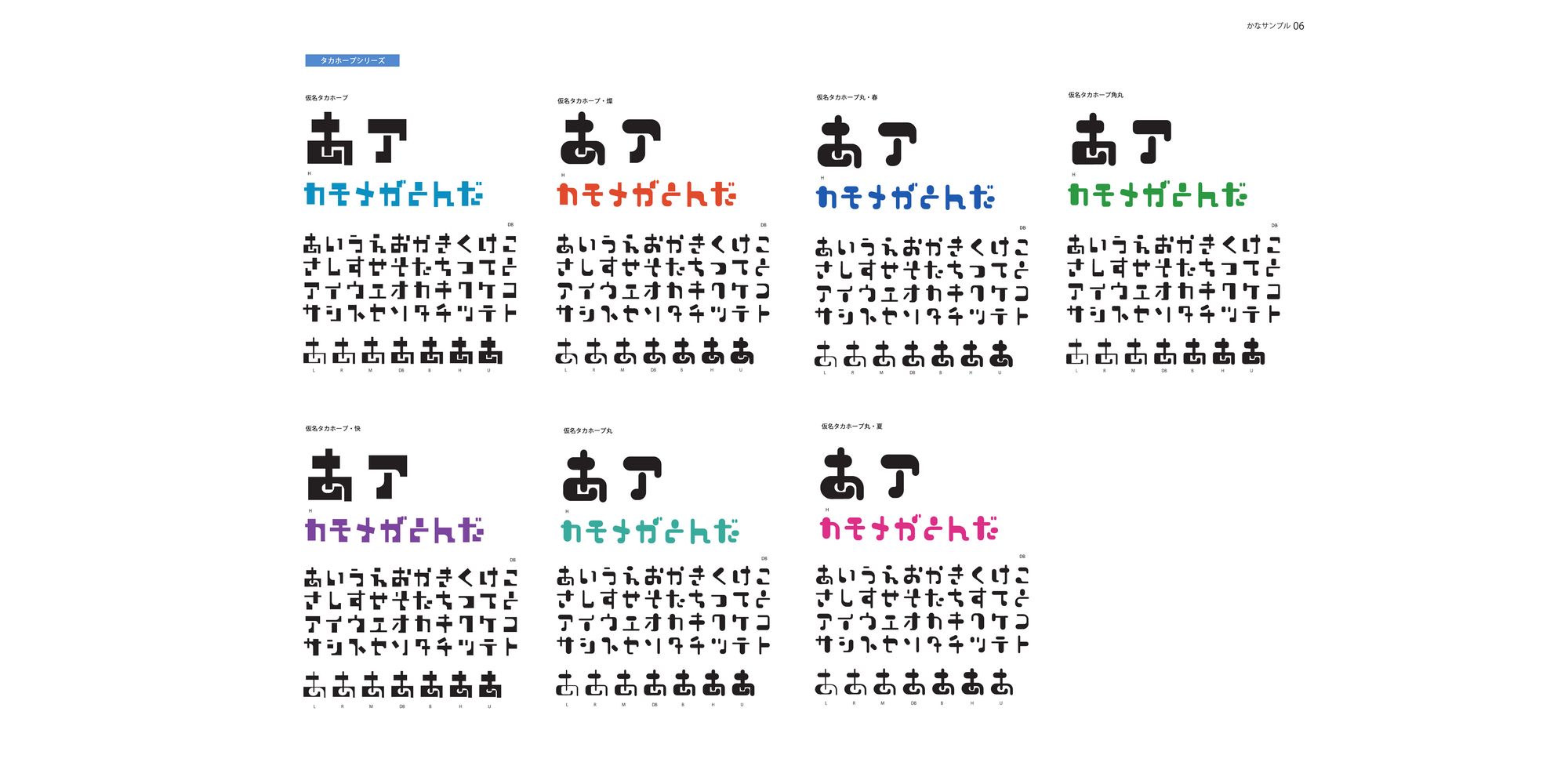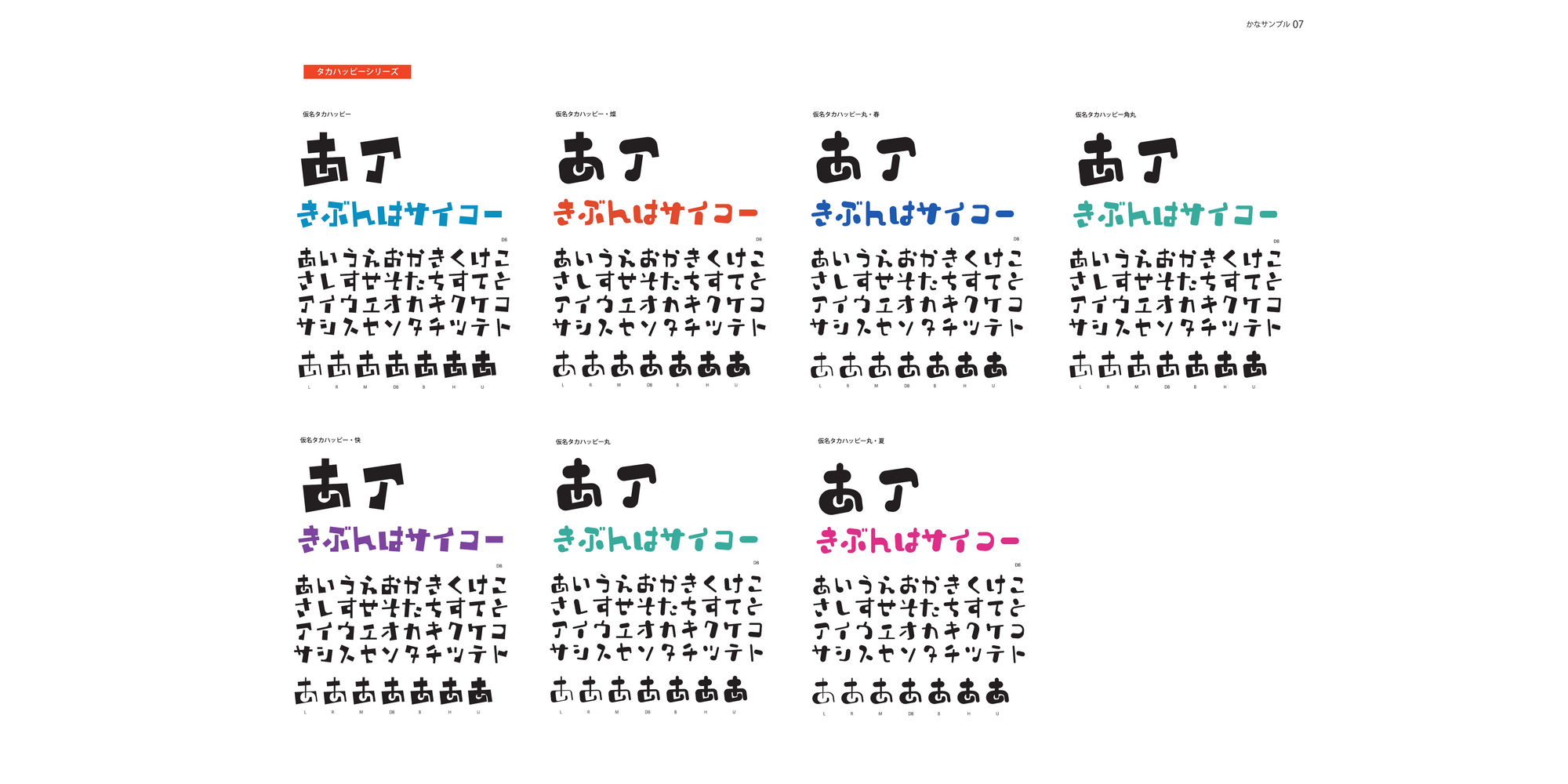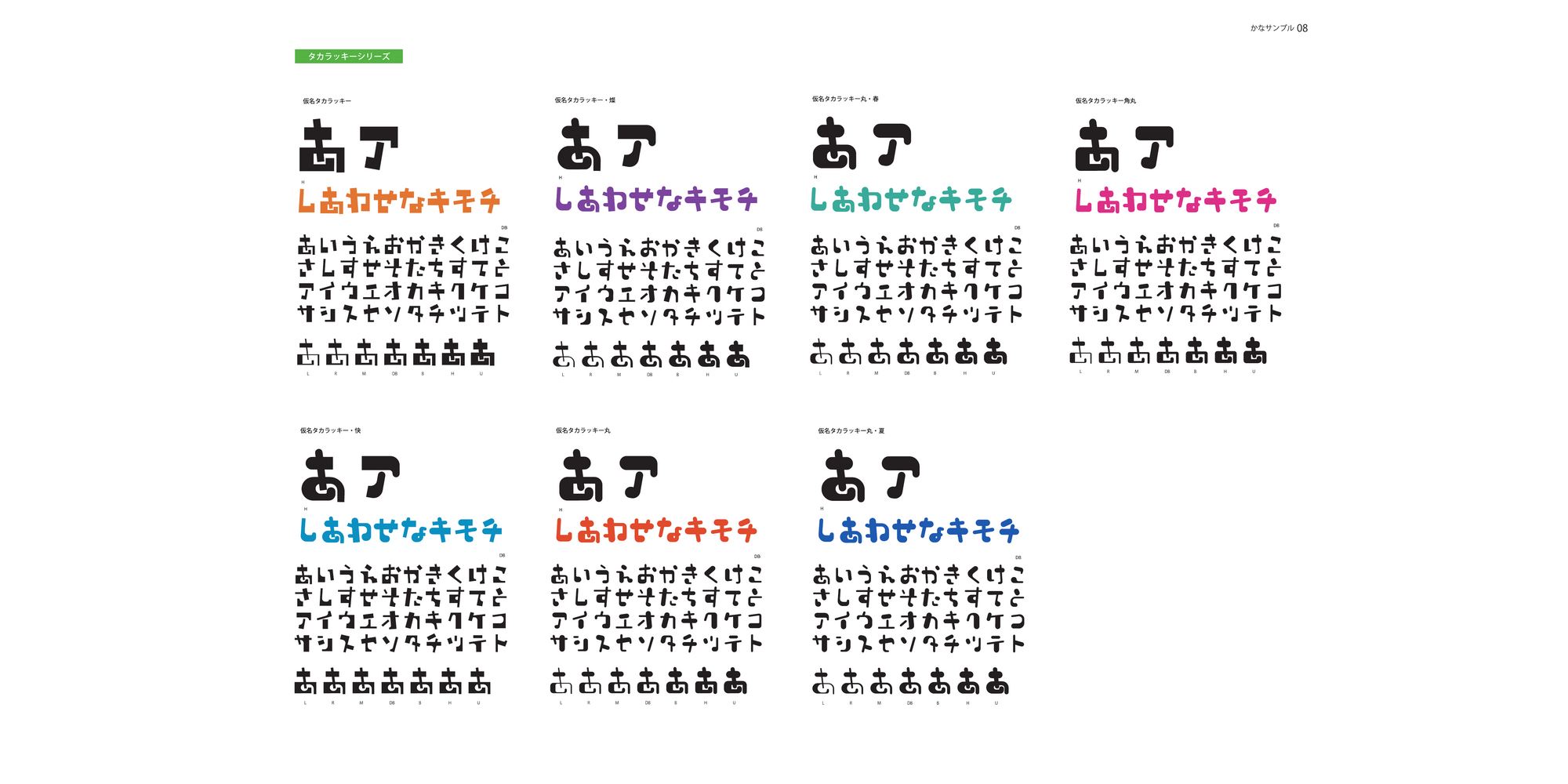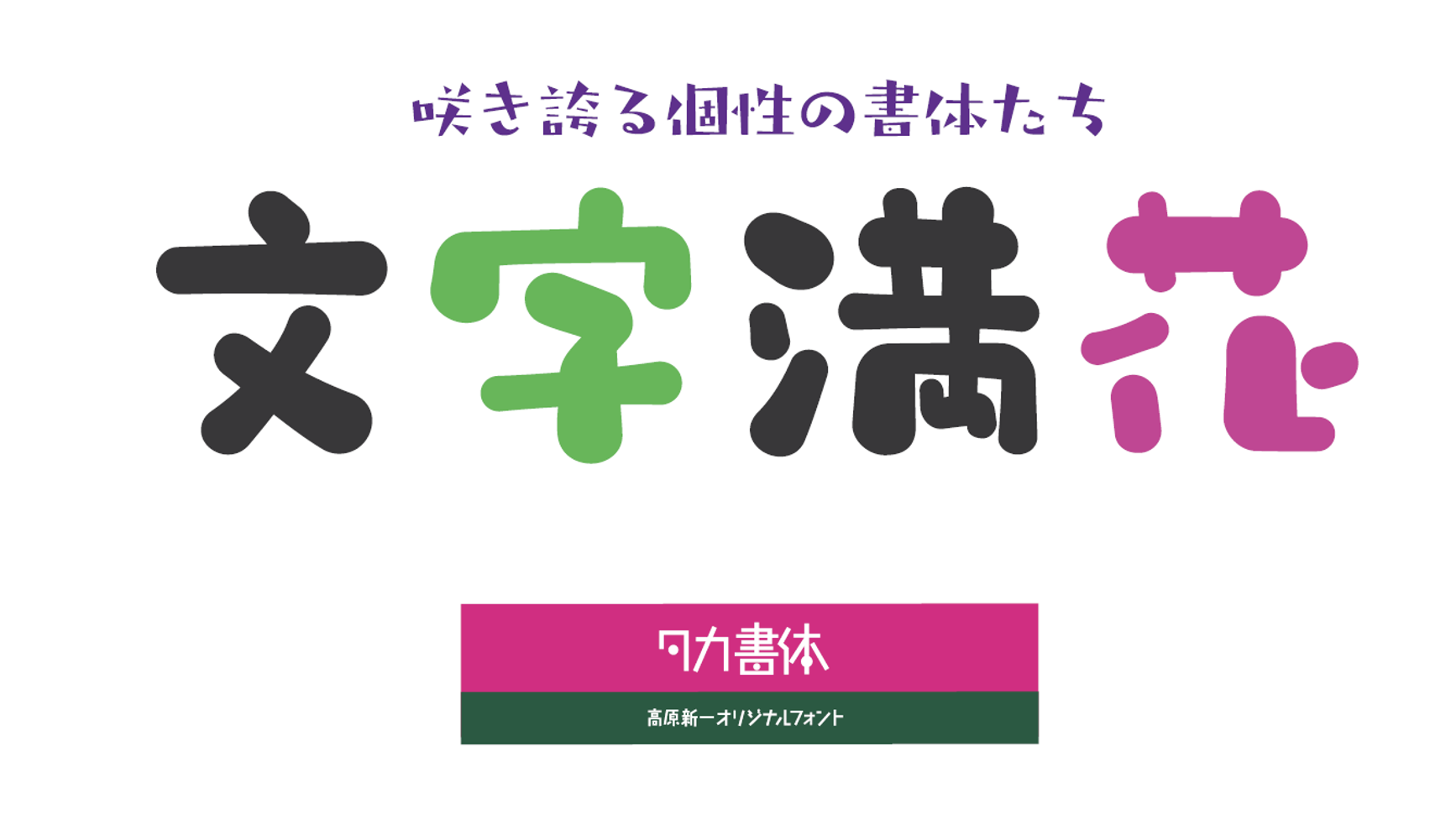
米国 Monotype Imaging Inc.の日本法人である Monotype株式会社(東京都港区、以下Monotype)は、タイプファウンダリ「たかデザインプロダクション」が手がける仮名書体67ファミリー、計469フォントを、フォントサービス「Monotype Fonts™」「フォントワークス® LETS®」、およびフォント販売サイト「MyFonts.com®」に新たに追加しました。
たかデザインプロダクションについて
たかデザインプロダクションは、書体デザイナーの高原新一氏が主宰するタイプファウンダリです。長年にわたり、広告や出版物をはじめとする幅広いデザインの現場で活用される、個性豊かな書体を制作しています。
全67ファミリー、469フォントを提供
今回追加されるのは、全67ファミリーの仮名書体です。幾何学的でモダンなものから、やわらかく親しみのあるもの、文字に動きや勢いを感じさせるものまで、多彩なデザインを取りそろえています。
各ファミリーには6~8ウエイトが用意されており、計469フォントの中から、制作物の目的や表現したい雰囲気に合った書体を選ぶことができます。
高原新一氏による「3シリーズ」の紹介
今回追加される書体のうち、仮名書体「仮名タカホープ」、仮名書体「仮名タカハッピー」、仮名書体「仮名タカラッキー」は、共通するデザインコンセプトから生まれた3つのシリーズです。
各シリーズには7種類のデザインバリエーションがあり、それぞれに7ウエイトを展開しています。3シリーズ合計で21ファミリー、147フォントを展開しています。
仮名書体「仮名タカホープ」
縦線と横線を基調に、線を整然と構成したシリーズです。線幅やバランスの異なる7種類のデザインから、用途に合った表情を選ぶことができます。
仮名書体「仮名タカハッピー」
仮名書体「仮名タカホープ」をベースに、文字の形や線に自由な角度を加えた、動きのあるシリーズです。楽しさや躍動感を演出したい場面に適しています。
仮名書体「仮名タカラッキー」
仮名書体「仮名タカホープ」の縦線・横線を基調とした構成に斜線を取り入れ、文字に動きとアクセントを加えたシリーズです。